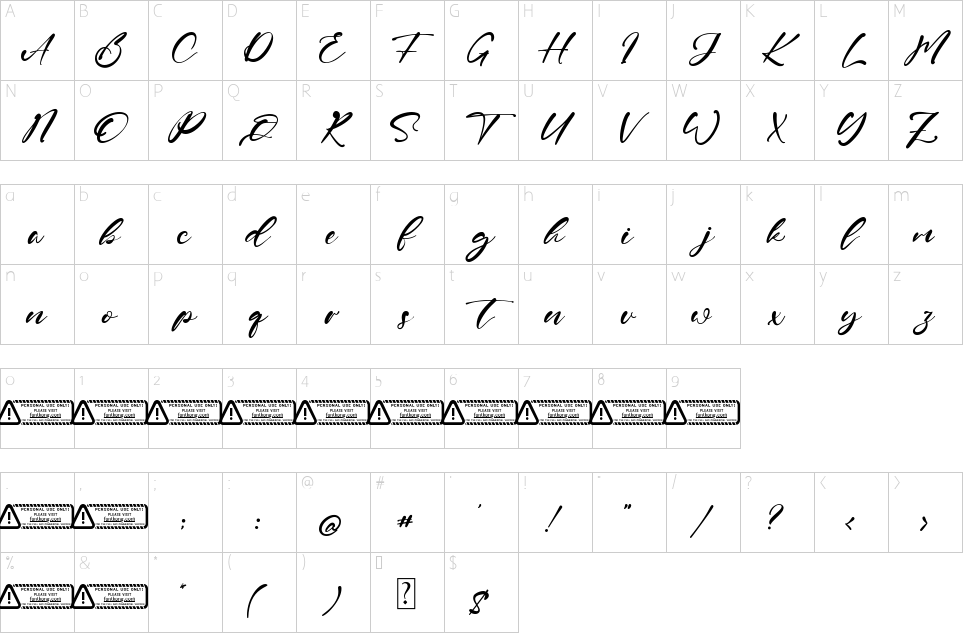
A Sandra Rolley Font é uma opção de fonte gratuita que traz uma dose de elegância e modernidade para seu próximo projeto visual. Desenhada por Font Kong, esta fonte é ideal para designers que buscam uma escolha de estilo neutro e elegante que não se distingue muito dos demais. Com uma presença clara e sinergia com textos, ela é perfeita para estilos de design que valorizam uma harmonia de cores e linhas. Descubra por si mesmo o charme desta fonte elegante. Com 2.246 downloads, muitos designers já aprovaram a Sandra Rolley Font. Ela é perfeita para criar uma paleta de textos moderna e acolhedora. Download a Sandra Rolley Font e experimente o poder desta fonte gratuita.